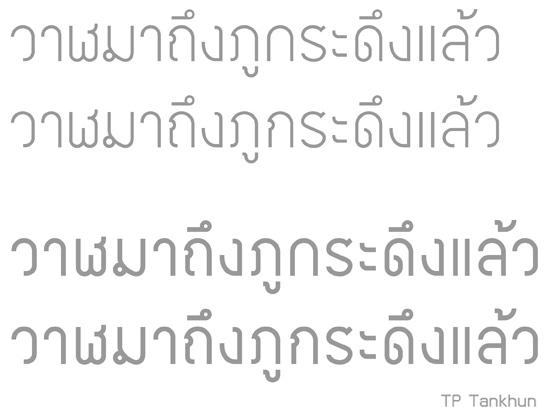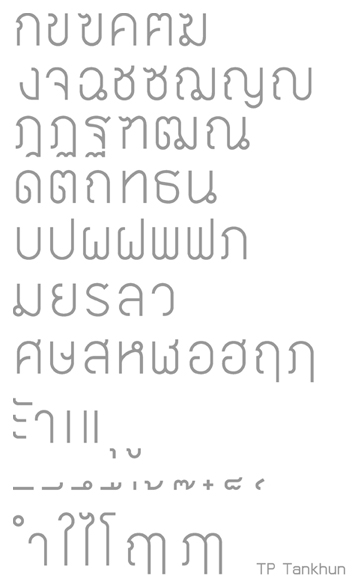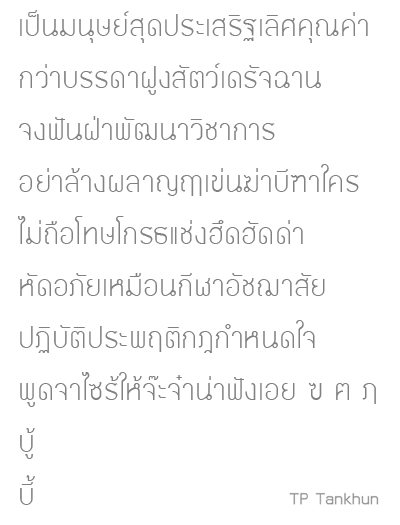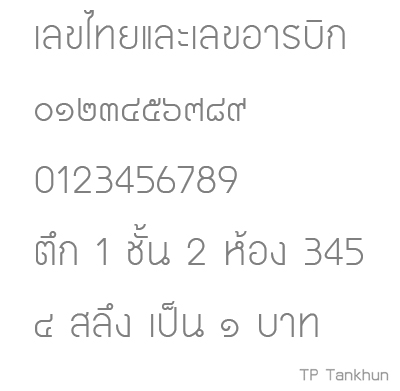
TP Tankhun
ภูกระดึงมาตาม request
ตอนทำ วาฬวาดชุดล่างที่เป็นตัวหนาก่อน ส่วนชุดบนตัวบางใช้ Offset path ให้ติดลบ
เพิ่งเห็นว่า ในชุดตัวบางสระอึมันก้อนโตประหลาดๆแฮะ
ก็ดูไม่แปลกนะ
แถมสวยดีด้วย
ชอบกอไก่มีปากครับ
ร มีกระดกขึ้นด้วยอ้ะ  :25:
(น่าจะมีกระดกลงด้วย แหะๆ)
แต่ทำสวยมากเลยอ้ะ  :25:
ไม่รู้ว่า อ อ่างที่อาจารย์เอกว่า หมายถึงแบบนี้รึเปล่า
เป็น version ปรับปรุงแล้ว
ภาษาไทยพิมพ์แล้วเป็นแบบนี้
ระยะบรรทัดมันห่างไปมั้ย คำว่าบู้บี้อย่างห่างเลย
ลองปรับค่าใน Metrics and Dimensions แล้ว ให้มันเกินสระอุล่างกับวรรณยุกต์บนนิดหน่อยแต่ก็ยังห่างอยู่
ทำยังไงอะ
ปรับตรงนี้ คิดว่าน่าจะใช่นะ  :26:
รู้สึกจะไม่ใช่มั้ง มันไม่เปลี่ยนแปลง ห่างเท่าเดิมเลย
ก ไก่ มีเว้าจงอยปาก ดูเข้ากันกับทั้งชุดมากกว่า(Mood & Tone)
แต่ประเด็นที่ผมบรรยายไว้ ก็ลองๆดูครับ จะเหมือนกันก็ได้ หรือ
จะต่างกันก็ได้ สุดท้ายต้องพิจารณารวมๆหลังจากมันเป็นชุดตัวพิมพ์แล้วครับ
เป็นฟอนต์ที่ใช้ได้จริงๆ ครับ สามารถเอาไปใช้กับงานสิ่งพิมพ์โดยไม่ขัดเขินได้เลย เยี่ยมมากๆ  :45:
รู้สึกกับ ล ลิง ส เสือ นิดหน่อยน่ะครับ มันต่างจากพวกยังไงบอกไม่ถูก